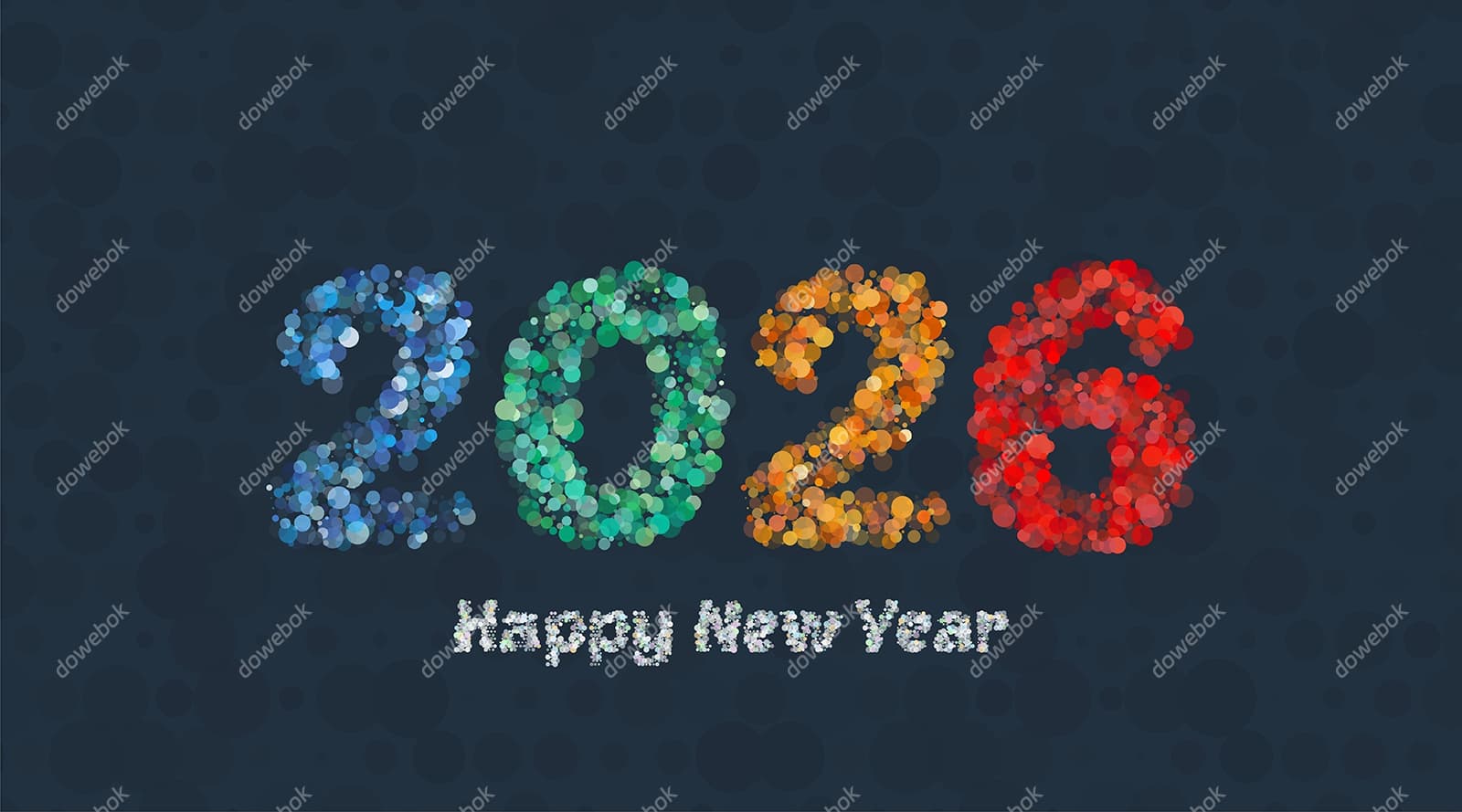
这是一款彩色颗粒拼接数字设计 2026 新年快乐矢量素材,深暗背景上,“2026” 由彩色颗粒拼接而成,从蓝到绿再到橙红渐变,灵动活泼。下方 “Happy New Year” 以白色碎粒呈现,与彩色数字形成柔和对比。整体以颗粒质感 + 渐变色彩,既显跨年的鲜活氛围,又用错落的颗粒形态透出轻松俏皮的节日质感,清新又亮眼。